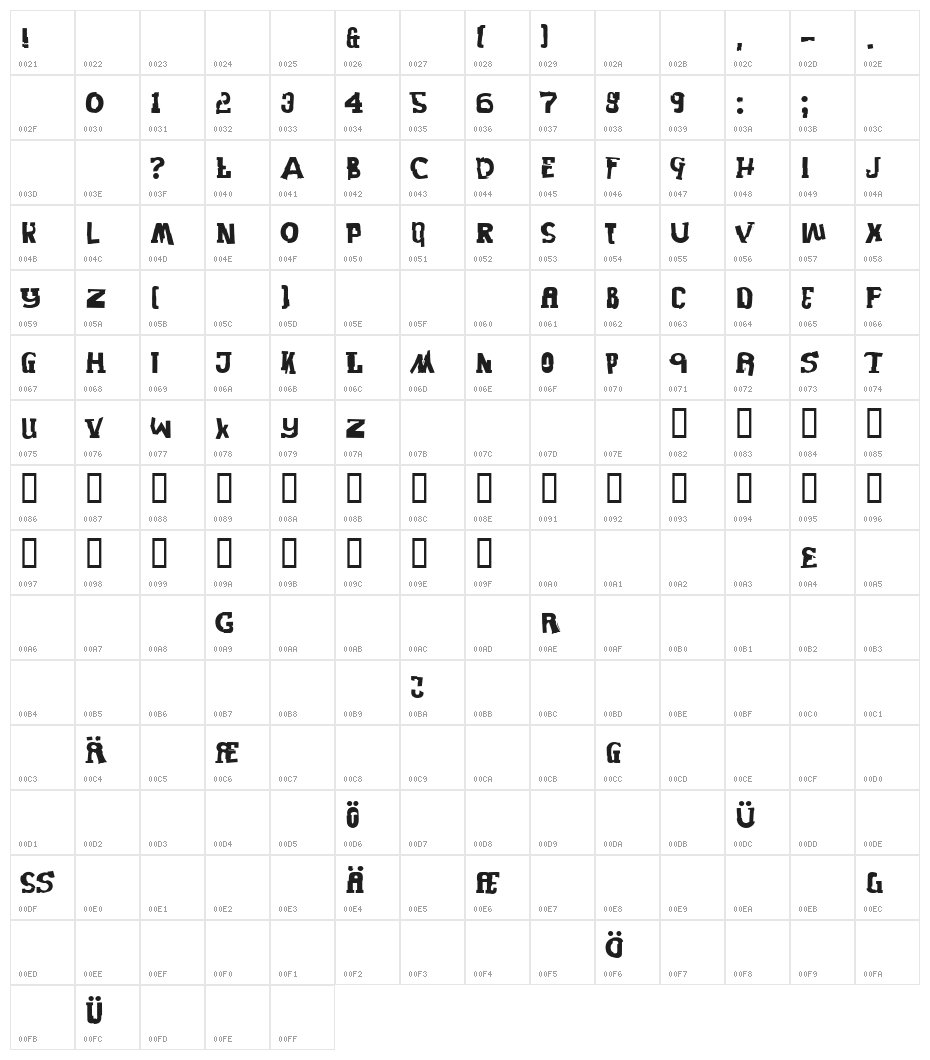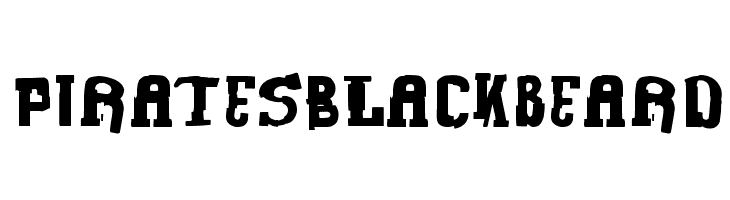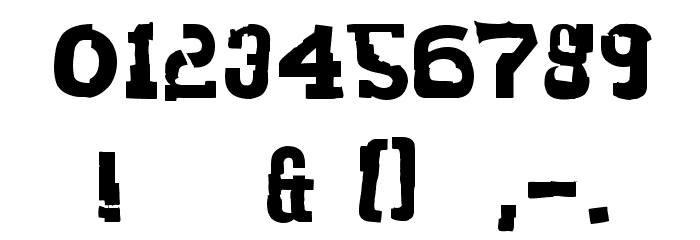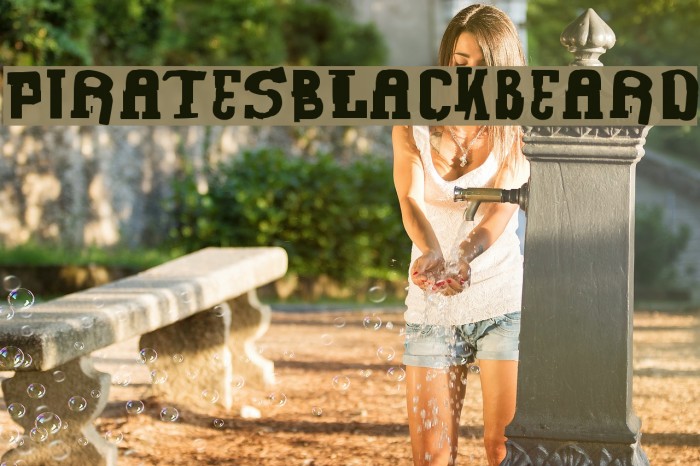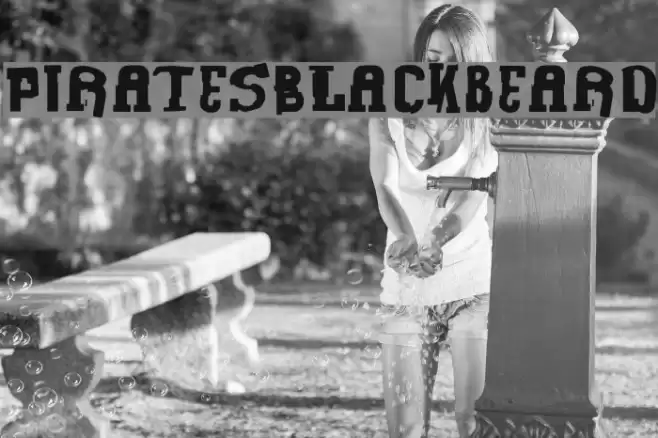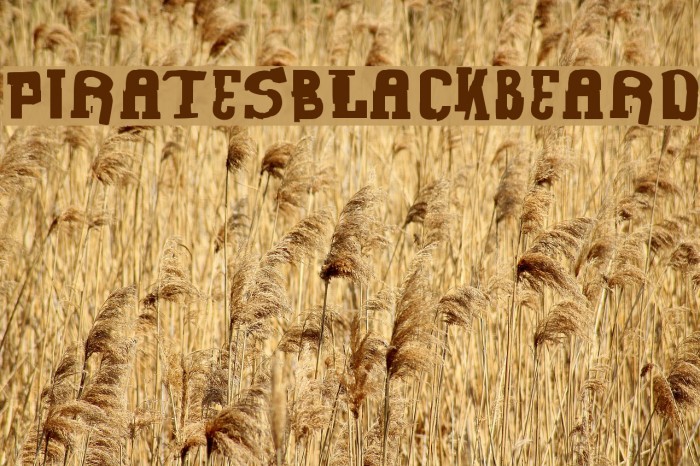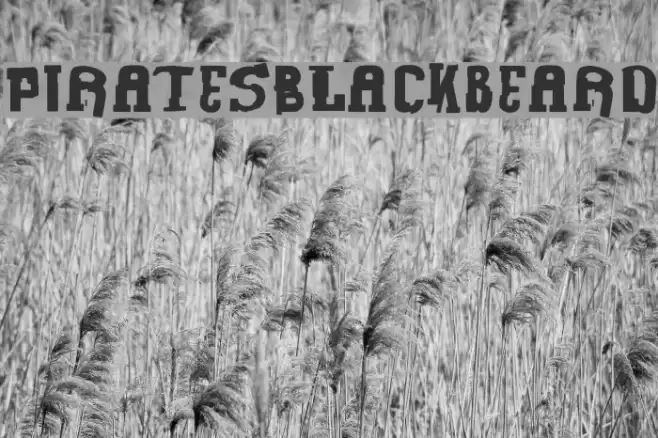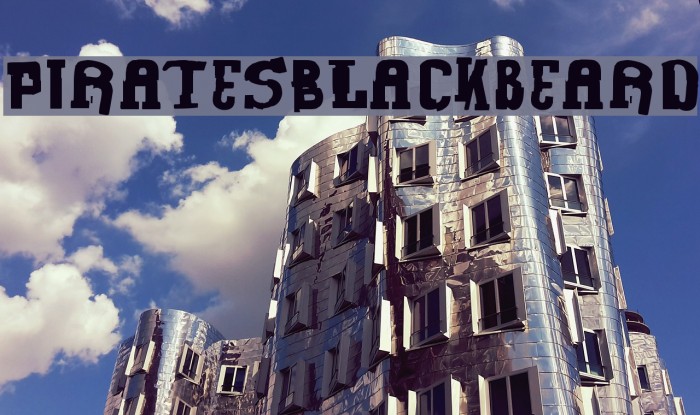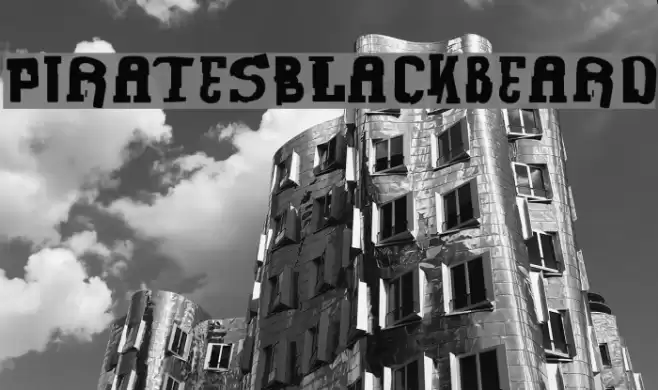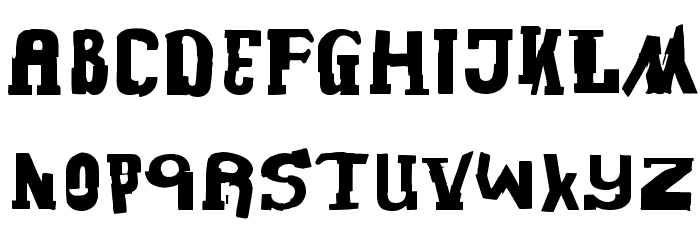
PiratesBlackbeard Font
| Caso de uso | Headlines, Logos, Themed Events |
| Proyectos propuestos | Ideal for pirate-themed events, adventure book covers, escape room branding, or any project needing a dramatic flair. |